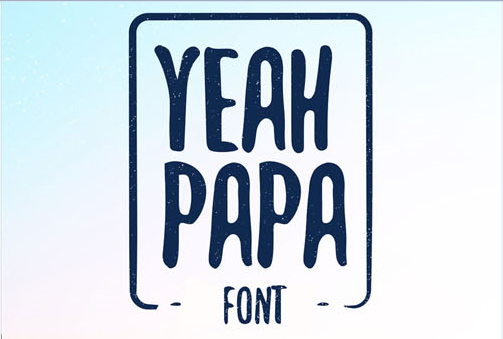
Yeah Papa Font – Download Grátis
A nova fonte ‘Yeah Papa Font’ traz uma atmosfera alegre e descontraída que se ajusta perfeitamente para o seu próximo projeto editorial ou design gráfico. Criada pelo designer Hamilton, essa fonte do tipo script é ideal para quando você precisa de um ar mais relaxado e informal em suas criações digitais. Com traços leves e uma tipografia fluida, a ‘Yeah Papa Font’ pode transformar qualquer texto em algo divertido e único. Suas letras vibrantes se adequam perfeitamente para aplicações como cartões personalizados, designs de logotipo ou até mesmo artigos de humor online. Não há dúvida de que essa fonte vai deixar seu design mais alegre e descolado. Se você está procurando por uma fonte divertida e original que dará um toque especial ao seu trabalho, ‘Yeah Papa Font’ é definitivamente para você. Combinada com sua categoria de script, esta fonte certamente será o ponto alto do seu próximo projeto.